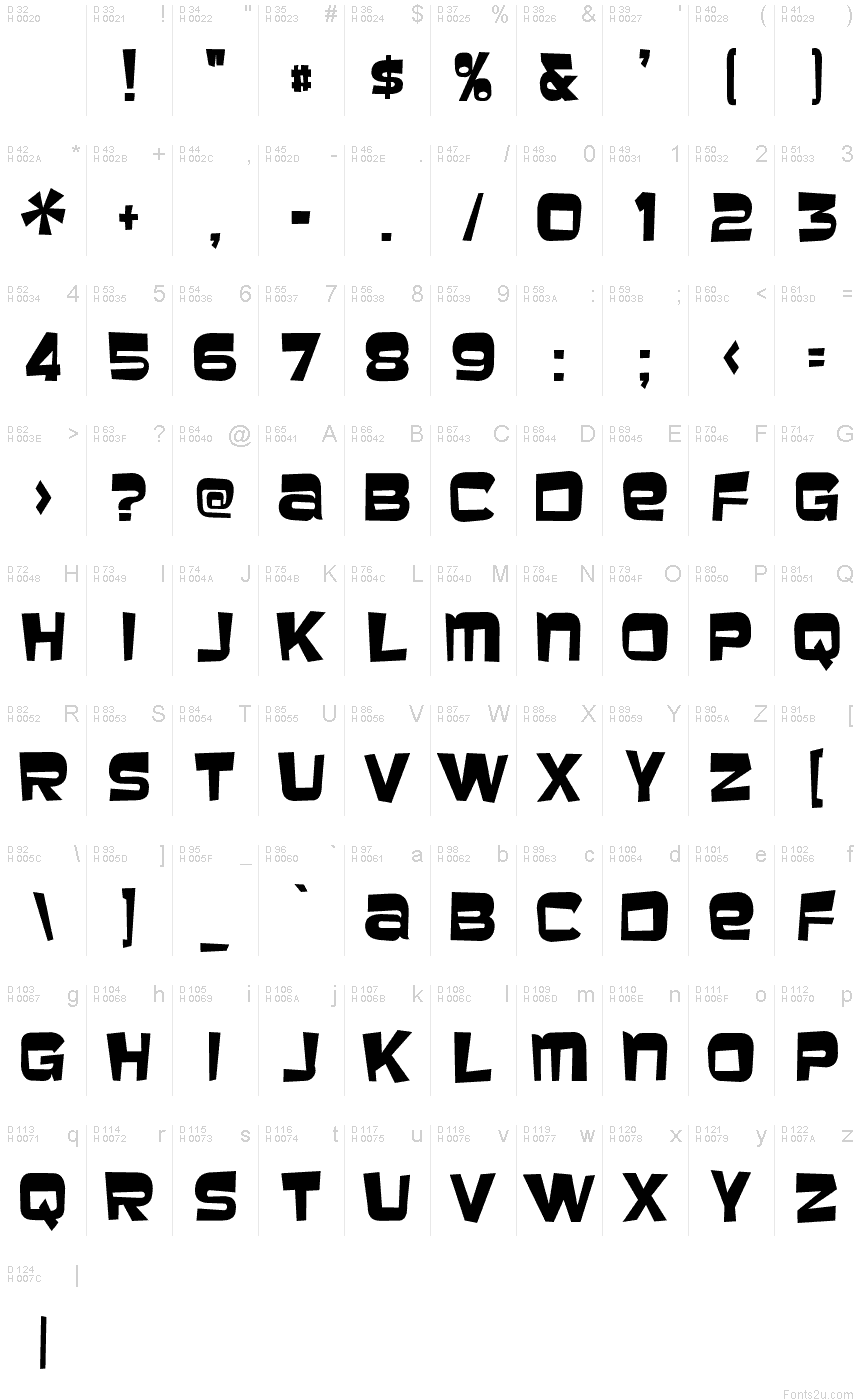
Die Baveuse von Ray Larabie ist eine kostenlose Comic-Display-Schriftart mit einem wunderbar klebrigen, handgezeichneten Charme. Die klobigen, klecksartigen Buchstaben wirken wie verlaufende nasse Farbe und verleihen Überschriften ein spielerisches Gefühl von Bewegung und Schabernack. Die lockeren Abstände und unebenen Konturen wirken spontan und unterhaltsam – so sieht alles, was du mit Baveuse gestaltest, ausdrucksstark, freundlich und ein bisschen wild aus.
Mit Baveuse bringst du Pepp in Kinderplakate, Partyeinladungen, Slime- oder Halloween-Grafiken, Comic-Cover, Süßigkeiten-Branding oder verspielte YouTube-Thumbnails. Diese kostenlose Schriftart glänzt vor allem in großen Formaten, wo ihr „tintentriefendes“ Wackeln und ihre fette Strichstärke richtig zur Geltung kommen. Kombiniere sie für den Fließtext mit einer klaren, schmalen serifenlosen Schrift, damit das Design lesbar bleibt, während Baveuse für das Chaos in Überschriften und Captions sorgt.